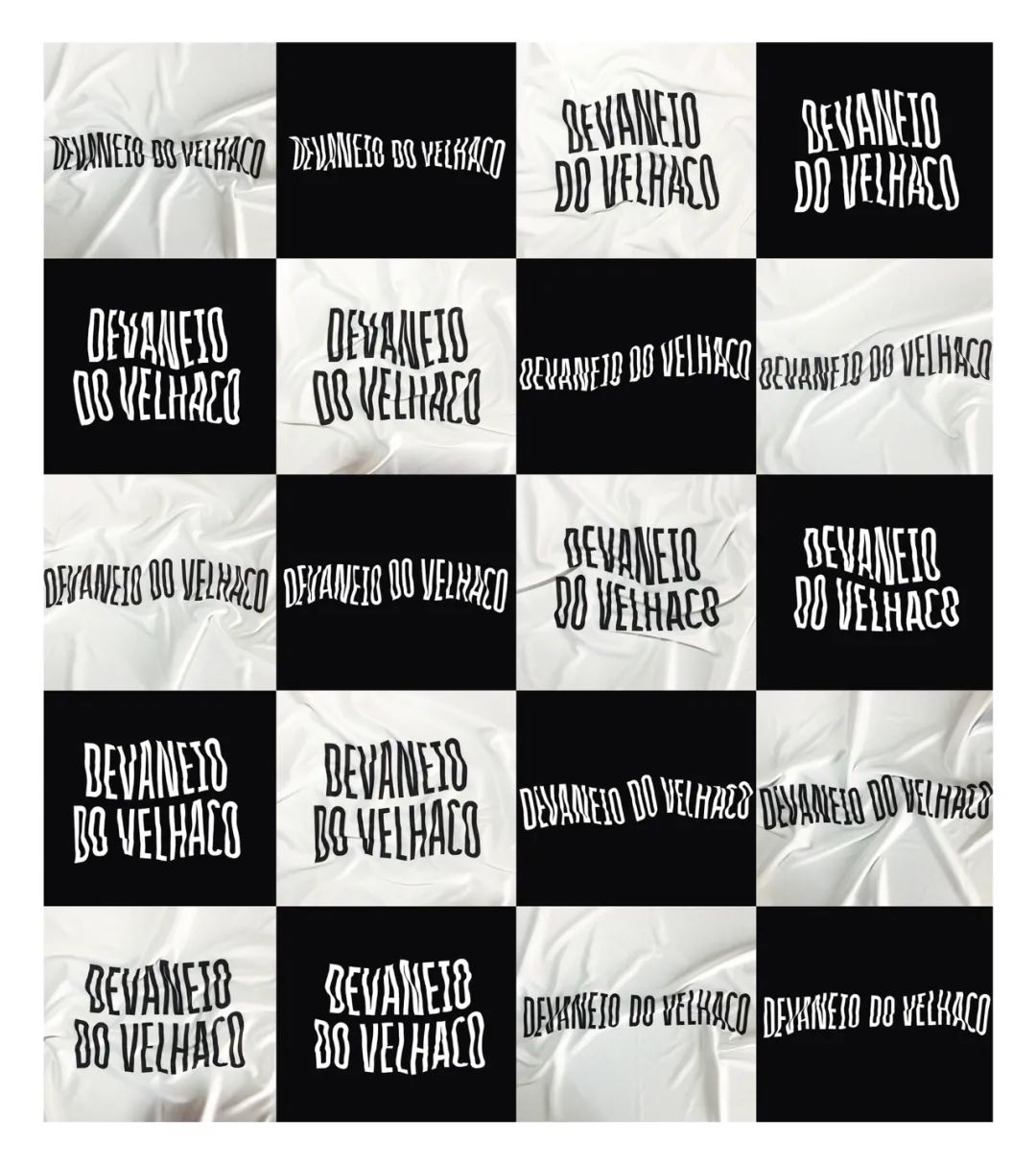
扭曲的字体应用案例分享,还可以这么玩?
Devaneio do Velhaco (Old Rogue's Daydream) 是一家酿酒酒吧,位于波尔图。
这家公司的想法从字面上说,是在一个梦中开始的:在与祖父萨尔瓦多的一次想象对话中,其中一位合伙人接到一项任务,要在该市历史中心的家族古董房里开一家酿酒厂。
有意思的是,对于该酒吧的品牌视觉设计,他们设计了一个独特的文字LOGO。
他们通过对织物的处理,使字体产生了不同的扭曲,直接引用了萨尔瓦多·达利的超现实主义。一起来看看他们玩字的过程。
上面是各种扭曲后的文字效果
看看名片
还有其他的设计应用
扭曲的文字
在酒吧夜店的场景下拍照
也是非常好看的
下面这个是门面设计
也是扭曲的招牌LOGO
回头率或被拍照晒照片的人一定很多
这类字体,视觉冲击力明显,节奏分明,可给人视觉上的震撼。
文字经过艺术化设计后,可以让文字形象变得情景化、视觉化、强化语言效果,对提升页面设计品质和视觉表现力发挥了极大性的作用。大家可以试一试,字体是挺好玩的。